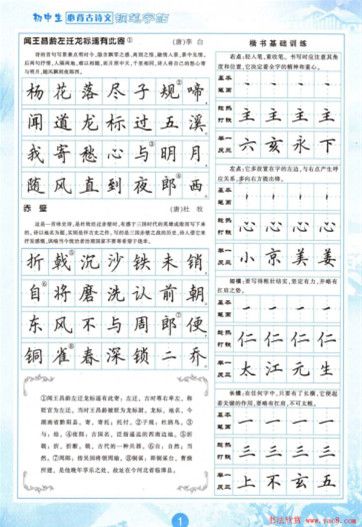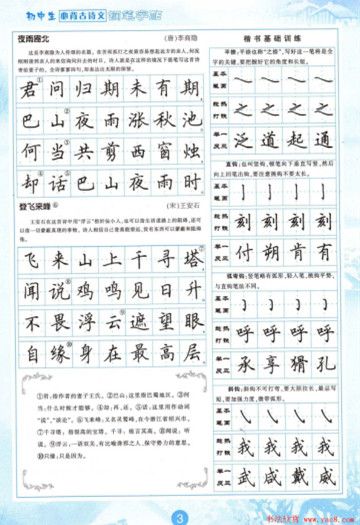
硬笔书法即狭义的钢笔练字是一门实用的艺术,学习硬笔书法,是提升广大学子综合素质(注意力、耐心、韧性、审美力等)的途径之一。对中小学生来说,写字的好坏还会影响自己的学习成绩、升学考试及毕业后的应聘等。为了配合写字教学,消除现在存在于广大学生群体中“只会打字,不会写字”的现象,西泠印社出版社编写了这套《国学经典名家硬笔练字字帖系列》,并特邀硬笔书法名家田英章教授书写。此次推出《小学生必背古诗文》、《初中生必背古诗文》、《高中生必背古诗文》等三本练字字帖,本篇仅提供《初中生必备古诗文》钢笔楷书字帖下载。
这三本练字字帖里所选古诗文皆出自教育部《全日制义务教育语文课程标准》指定必背篇目,以使广大学生群体在提高练字书写水平的同时,提高自己的国学修养与文化素质,并巩固课堂知识,提高学习成绩。此外,这三本练字字帖在书写上,也有一个由易到难,由偏正楷字体到偏草字体的递进过程,以更好地引导中小学生循序渐进地练好字,提高汉字的书写质量,并逐步在书写质量有保障的前提下提高书写的速度,达到又快又好的练字目的。